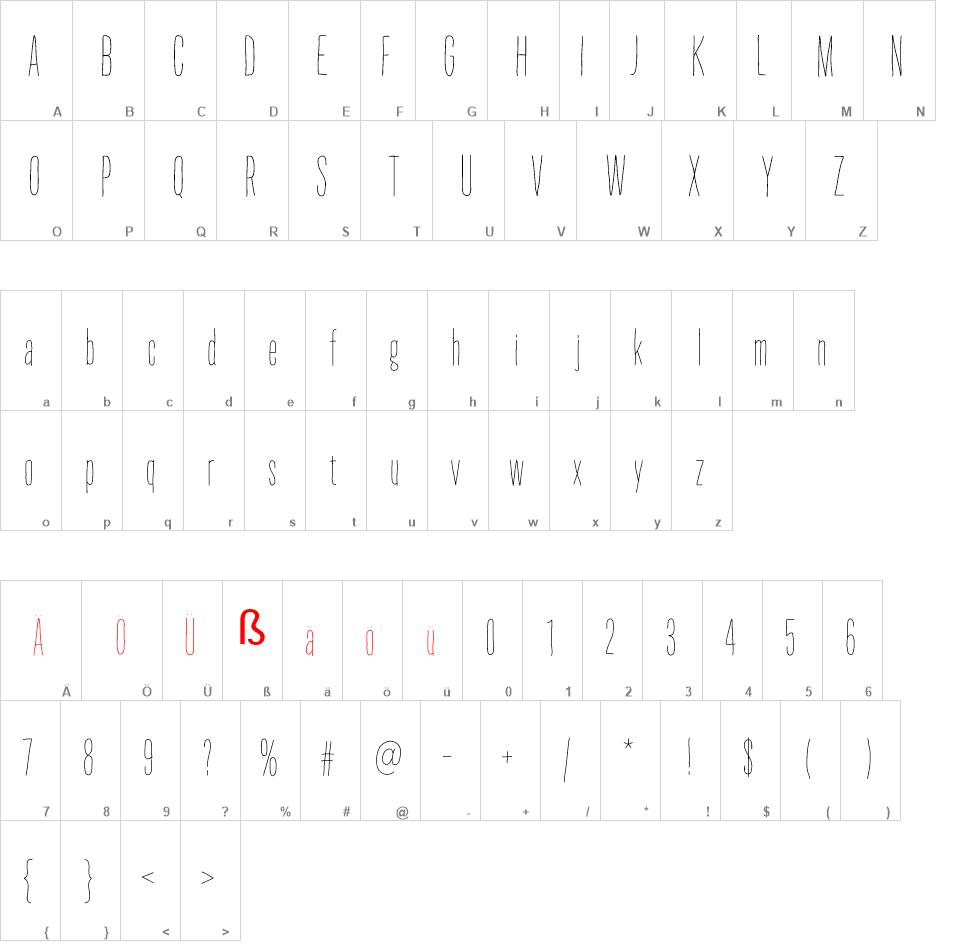
Thin Fingers
Thin Fingers font
Thin Fingers
Thin Fingers ist eine unglaublich edle handschriftliche Schrift, die dank einer starken Lesbarkeit sofort ins Auge fällt.
Sehr gestreckt und dünn, ist es ideal für jedes Titelmaterial (speziell in Anzeigen, Buchdeckel), sei es für den Druck oder für digitale Zwecke.